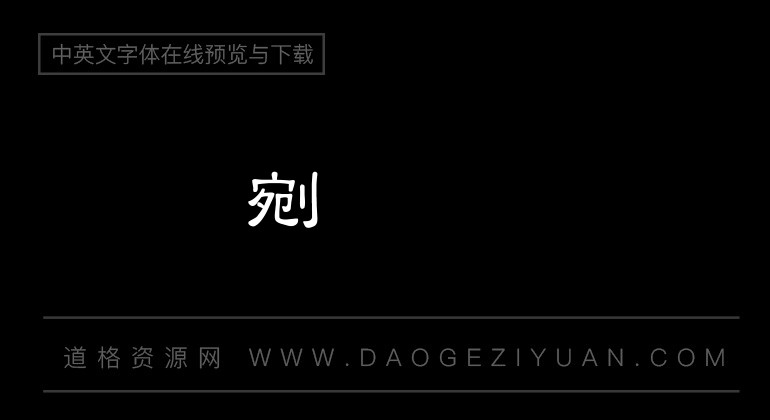
富汉通中隶书体繁是一种以中隶书体为基础的字体,由富汉通公司开发,可以支持繁体中文排版。它具有优秀的精细度、高可读性和美观的设计,可以让您的文字更加清晰、精致。它的字体设计和排版技术能够满足您对文字的任何要求,让您的文字更加精美、简洁、大方。文件名:FuHanTongZhongLiShuTiFan-1.ttf
富汉通中隶书体繁是一款非常不错的手写艺术字体,具有很好的视觉感,适合于文化类的宣传设计、商业类品牌的广告和产品包装设计以及个性化文字排版等较多场景。